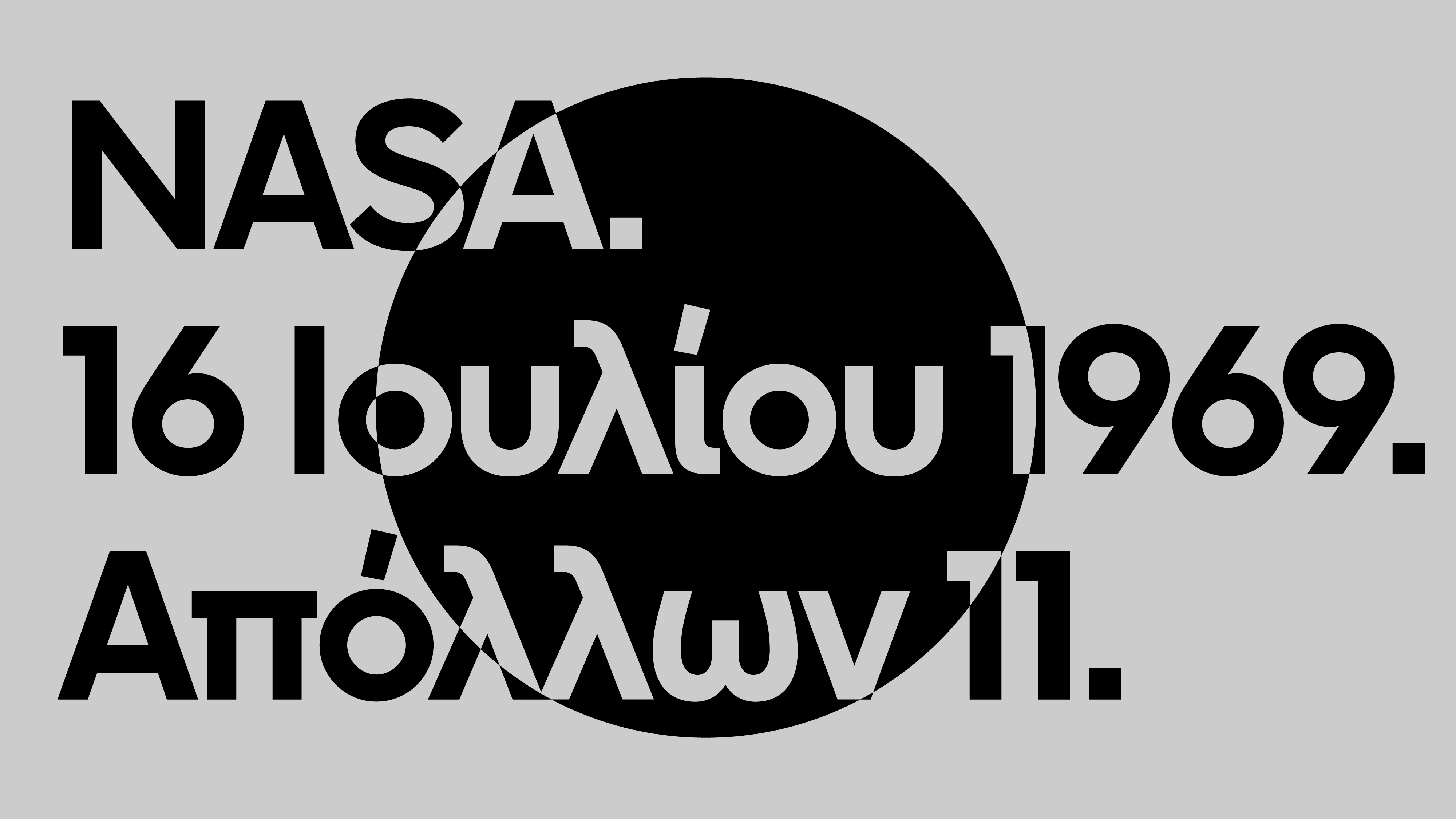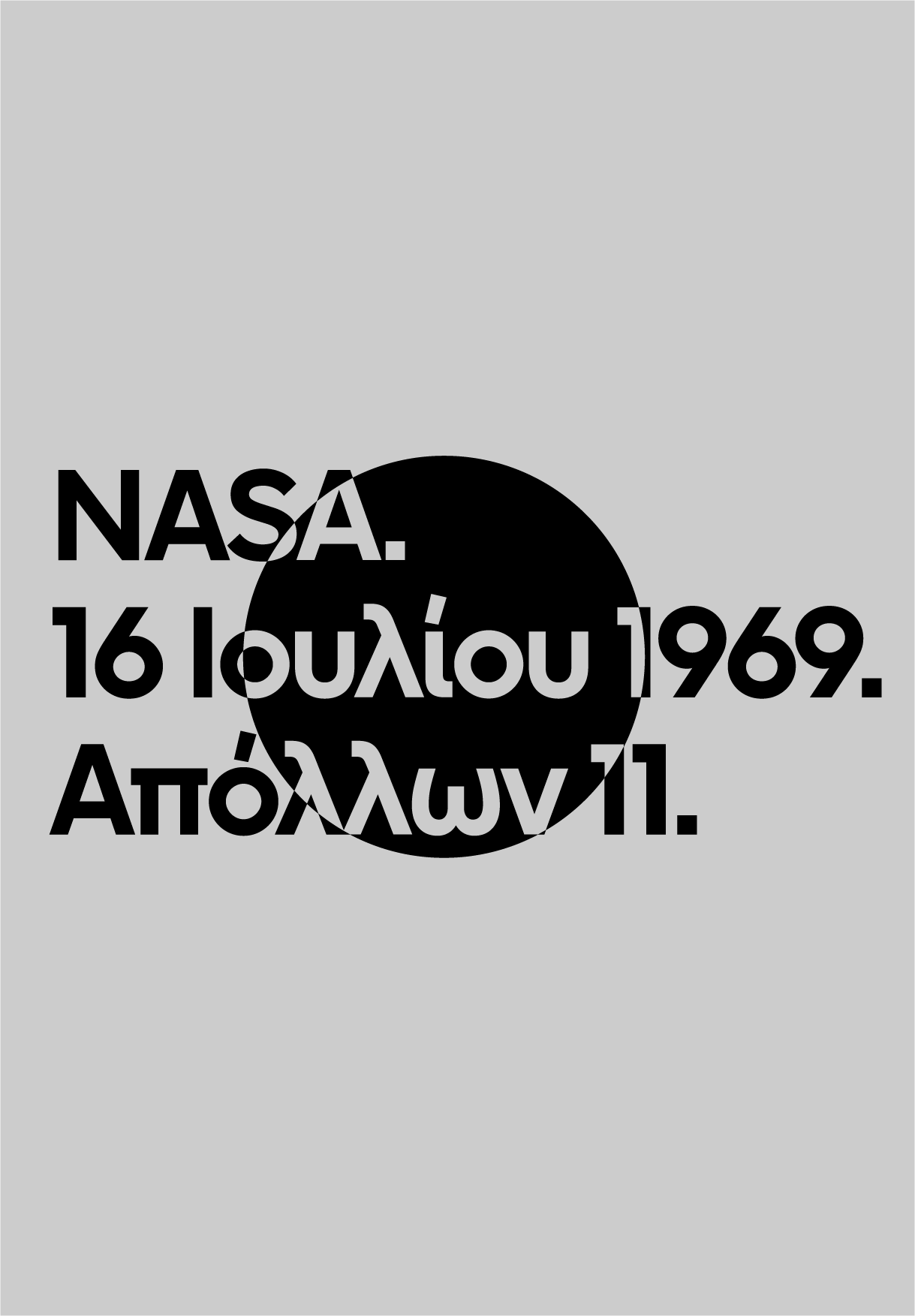
F37 Moon Greek Font Sampler
Το F37 Moon έχει μεγάλο ύψος X, δίνοντάς του μια εξαιρετικά καθαρή και εξαιρετικά μινιμαλιστική εμφάνιση. Το κοντό σώμα της γραμματοσειράς δημιουργεί μια συμπαγή και τολμηρή εμφάνιση.